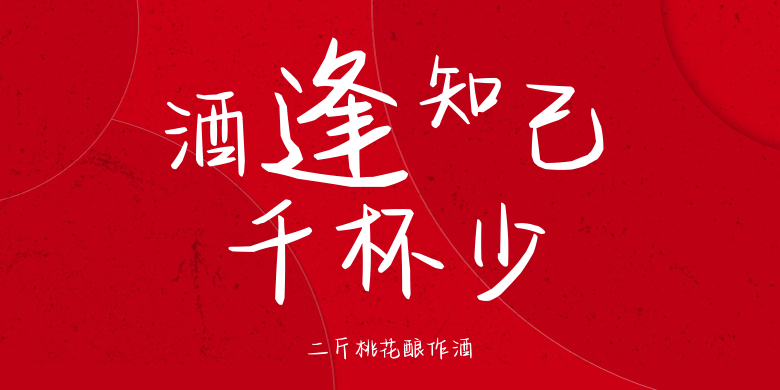
二斤桃花酿作酒
二斤桃花酿作酒,这款字体结构工整、笔画清晰,兼顾美观与易读性,适用于标题、正文、海报、包装、LOGO 等多种场景。字形优雅稳定,风格百搭耐看,适配日常排版与创意设计,让文字呈现更舒适、更具质感。二斤桃花酿作酒一笔一画,皆是细节,以均衡的比例、流畅的线条打造舒适视觉体验,字形端正大气,风格简约现代。无论是商业设计、品牌宣传还是日常排版,都能轻松驾驭,让文字更有格调与力量。二斤桃花酿作酒字体下载。